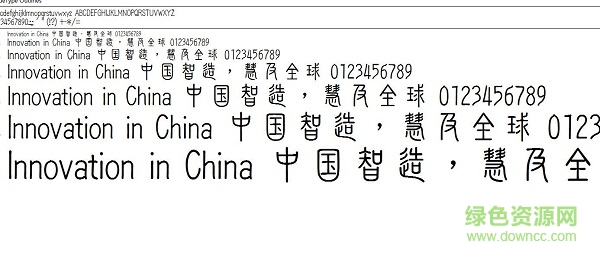
軟件介紹 軟件標簽: 華康字體 字體 dfnewchuan md hkp bf字體又叫華康新篆體,是一款極具美感的篆書字體,挺拔蒼勁,肅穆端莊,帶有古典氣息,適用于藝術(shù)設(shè)計方面,歡迎大家來綠色資源網(wǎng)免費下載!華康字體推薦dfpsongw3 授權(quán):免費軟件 WinAll, WinXP, Win7大小:1.3M語言:中文dfpsongw3字體也叫華康宋體w3(p),w3是華康宋體系列字體中最細的一款,該字體外形秀氣,筆畫干凈,可以用于正文排版、雜志讀物、網(wǎng)頁設(shè)計等領(lǐng)域,報版歡迎免費下載!篆書字體介紹【秦篆】大篆是周宣王時對古文字整理之后的一種文字,因經(jīng)史籍之手。故又稱“下載地址dfpsongw12 gb5 授權(quán):免費軟件 WinAll, WinXP, Win7大?。?.3M語言:中文dfpsongw12字體就是華康宋體w12字體的英文名稱,該字體筆畫粗細勻稱,字型嚴謹,筆道流暢,整體大方得體,有需要者歡迎在綠色資源網(wǎng)下載!dfpsongw12字體安裝方法文字添加方法: 第一種 1.下載字體并解壓縮; 2.開始中打開控制面板下載地址篆書字體介紹【大篆】指金文、籀文、六國文字,它們保存著古代象形文字的明顯特點【小篆】也稱“秦篆”,是秦國的通用文字,大篆的簡化字體,其特點是形體均勻齊整、字體較籀文容易書寫。dfnewchuan字體安裝方法方法一:控制面板/字體/文件/安裝新字體;方法二:直接將字體復制到C:\WINDOWS\Fonts。 軟件截圖 上一張下一張(1 / 1) 安裝詳細截圖 其他版本下載 標題 大小 更新日期 下載 下載地址 電腦版 dfnewchuan md hkp bf 點擊報錯 軟件無法下載或下載后無法使用,請點擊報錯,謝謝! 關(guān)閉報錯反饋 請描述您所遇到的錯誤,我們將盡快予以修正,謝謝! *必填項,請輸入內(nèi)容 本類最新 華康漆隸體繁w5 wow魔獸世界華康少女字體ttf 免費版 華康蕓風體w3 繁體 華康pop2體w9 p 華康粗黑體繁 dfpyuanw7字體 ttf版 相關(guān)文章 Photoshop字體安裝使用方法和技巧 如何解決“無法新增字體”問題 Win 7系統(tǒng)安裝字體方法 網(wǎng)頁字體大小設(shè)置方法 怎么改網(wǎng)頁字體大小 在Linux系統(tǒng)中安裝字體的幾種方法 windows7字體顯示問題:打開某些程序的時候顯示的是亂碼 用戶評論 熱門評論 最新評論 發(fā)表評論 查看所有評論(0) 昵稱: 請不要評論無意義或臟話,我們所有評論會有人工審核. 字數(shù): 0/500 (您的評論需要經(jīng)過審核才能顯示)